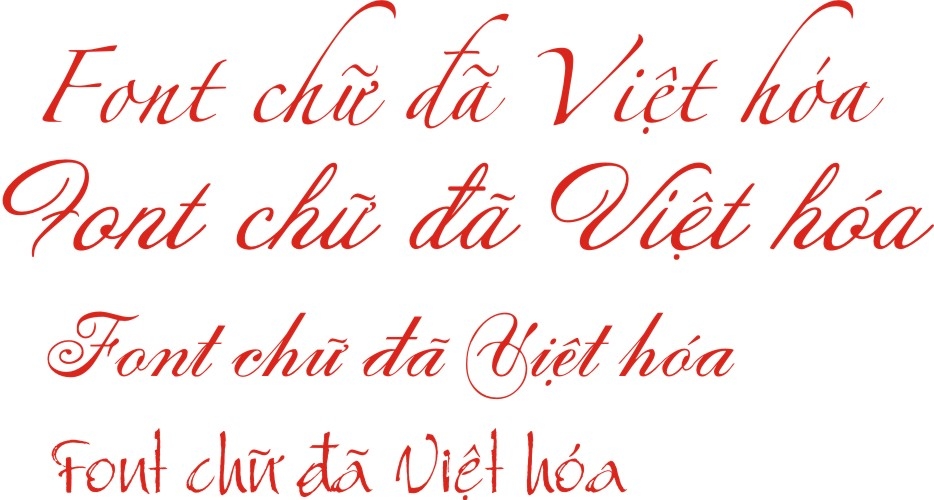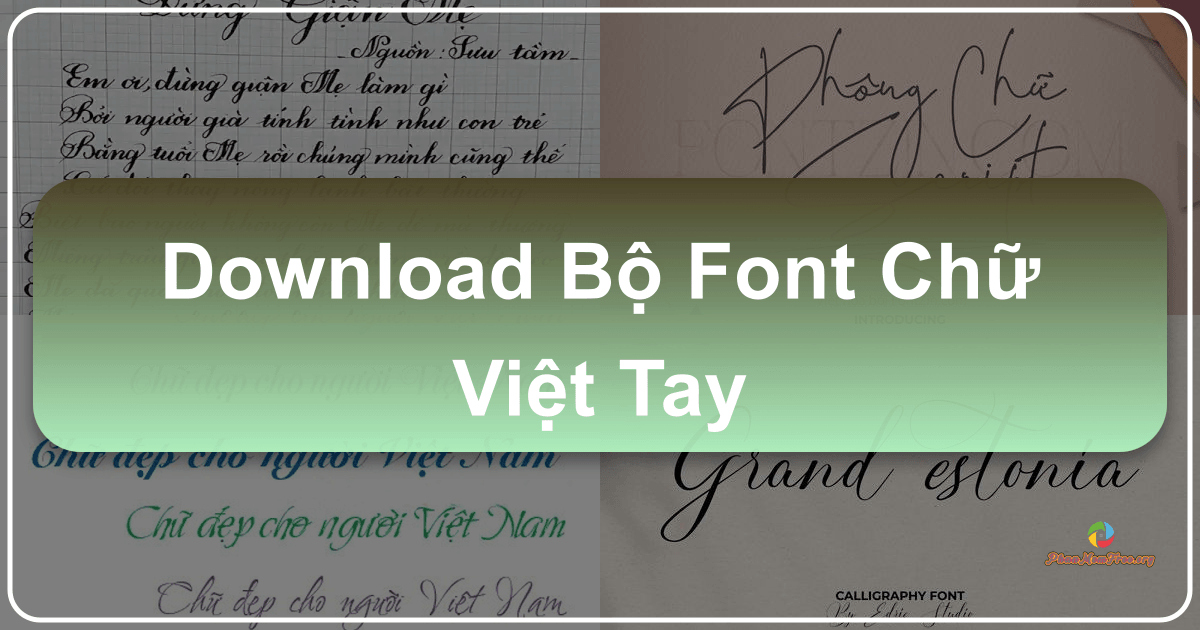
Trong thế giới kỹ thuật số ngày nay, nơi sự chính xác và tính chuyên nghiệp của phông chữ máy tính được đặt lên hàng đầu, việc tìm kiếm một phông chữ mang đậm dấu ấn cá nhân, thể hiện sự gần gũi và ấm áp lại càng trở nên giá trị. Bộ Font chữ viết tay, một sản phẩm miễn phí dành cho hệ điều hành Windows, chính là câu trả lời cho nhu cầu đó. Bộ font này mang đến cho người dùng trải nghiệm độc đáo, cho phép họ thỏa sức sáng tạo bằng cách sử dụng các kiểu chữ mô phỏng chữ viết tay, mang đến một hơi thở mới mẻ và đầy cảm hứng cho các tác phẩm thiết kế, văn bản hay bài học của mình.
Sự kết hợp hoàn hảo giữa truyền thống và hiện đại:
Bộ Font chữ viết tay không đơn thuần chỉ là một tập hợp các phông chữ. Đó là một kho tàng sáng tạo, nơi sự tinh tế của nét chữ viết tay được kết hợp khéo léo với sự tiện lợi của công nghệ máy tính. Thay vì những phông chữ máy tính cứng nhắc, bộ font này mang đến sự mềm mại, tự nhiên, gần gũi như thể những dòng chữ được viết ra từ chính bàn tay của người dùng. Sự kết hợp này tạo nên một sức hút đặc biệt, dễ dàng chinh phục người xem bằng vẻ đẹp giản dị mà đầy cuốn hút.
Ứng dụng đa dạng, đáp ứng mọi nhu cầu:
Khả năng ứng dụng của Bộ Font chữ viết tay vô cùng đa dạng và linh hoạt. Từ việc tạo ra những tấm thiệp chúc mừng ý nghĩa, những bài đăng trên mạng xã hội thân thiện cho đến việc thiết kế những ấn phẩm quảng cáo độc đáo, bộ font này đều có thể đáp ứng một cách xuất sắc. Đặc biệt, đối với các giáo viên, đây là một công cụ hỗ trợ đắc lực trong việc viết mẫu cho học sinh, giúp truyền đạt kiến thức một cách sinh động và gần gũi hơn.
Sự đa dạng về kiểu chữ trong bộ font cũng là một điểm cộng đáng kể. Không chỉ đơn thuần là một vài kiểu chữ viết tay thông thường, bộ font này cung cấp nhiều lựa chọn phong phú, cho phép người dùng thỏa sức lựa chọn kiểu chữ phù hợp nhất với từng mục đích sử dụng. Điều này giúp người dùng có thể dễ dàng thể hiện cá tính và phong cách riêng của mình trong từng tác phẩm.
Khơi nguồn cảm hứng sáng tạo bất tận:
Yếu tố sáng tạo luôn đóng vai trò then chốt trong lĩnh vực thiết kế. Bộ Font chữ viết tay chính là nguồn cảm hứng dồi dào, giúp các nhà thiết kế và những người yêu thích sáng tạo có thể thỏa sức bay bổng với trí tưởng tượng của mình. Khác với những phông chữ máy tính quá đơn điệu và quen thuộc, bộ font này mang đến một luồng gió mới, một nét độc đáo riêng biệt, giúp tạo điểm nhấn ấn tượng cho các tác phẩm. Dù không mang vẻ cầu kỳ như phông chữ thư pháp, nhưng sự tự nhiên, giản dị của chữ viết tay lại mang đến một sức hút riêng, thu hút sự chú ý của người xem một cách tự nhiên và tinh tế.
So sánh với các bộ font khác:
Mặc dù hiện nay có nhiều bộ font chữ tiếng Việt khác nhau, bao gồm cả một số font chữ viết tay, nhưng Bộ Font chữ viết tay vẫn có những ưu điểm nổi bật riêng. Khác với các bộ font chữ khác, bộ font này tập trung hoàn toàn vào việc mô phỏng chữ viết tay, cung cấp nhiều lựa chọn đa dạng về kiểu chữ, đảm bảo người dùng dễ dàng tìm thấy kiểu chữ phù hợp nhất với nhu cầu của mình.
Google cũng đã thiết kế riêng cho tiếng Việt một bộ font chữ đơn giản, mang dáng dấp của Google Sans. Tuy nhiên, Bộ Font chữ viết tay vẫn khác biệt với sự đa dạng hơn về kiểu chữ và tính cá nhân hóa cao hơn. Mỗi font chữ trong bộ font này đều có nét đặc trưng riêng, giúp tạo nên sự độc đáo và thu hút cho các tác phẩm.
Kết luận:
Bộ Font chữ viết tay là một lựa chọn tuyệt vời cho những ai đang tìm kiếm một bộ font chữ độc đáo, mang đậm dấu ấn cá nhân. Với sự đa dạng về kiểu chữ, tính dễ sử dụng và hoàn toàn miễn phí, bộ font này hứa hẹn sẽ là một công cụ đắc lực, giúp người dùng thỏa sức sáng tạo và tạo nên những tác phẩm ấn tượng. Hãy tải ngay bộ font này và trải nghiệm sự khác biệt mà nó mang lại! Bộ font không chỉ là một công cụ, mà còn là một nguồn cảm hứng giúp bạn thể hiện cá tính và tạo nên những điều tuyệt vời. Hãy để những nét chữ viết tay mềm mại, tự nhiên này tô điểm thêm cho những tác phẩm của bạn và khiến chúng trở nên sống động hơn bao giờ hết.